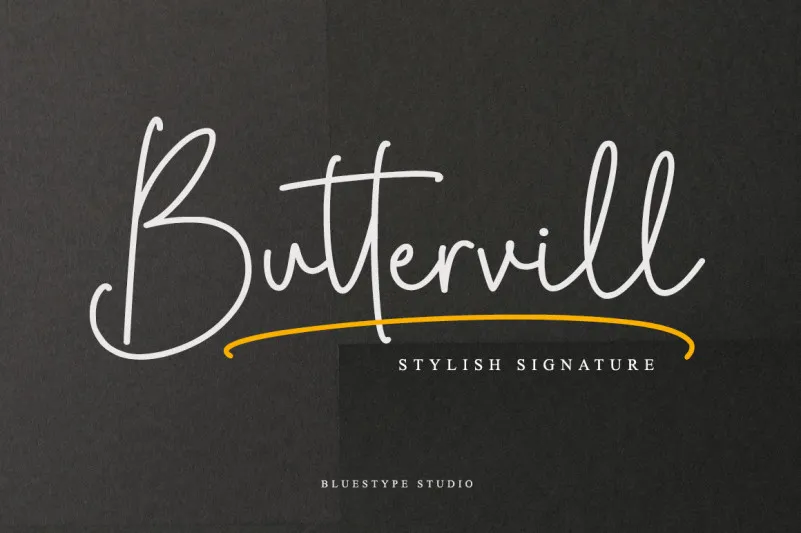
Estamos muito felizes com a sua visita ao site onde você pode baixar a Buttervill Signature Font, uma fantástica fonte de script que traz um toque pessoal para seus projetos. Esta é uma linda e simples fonte criada por f0rdesigner, inspirada no estilo da Bluestype Studio. O design desta fonte de texto faz com que ela seja perfeita para adicionar um ar autêntico a vários tipos de projetos. Que isso possa ser cartazes, convites ou até mesmo letras em sua próxima criação gráfica. A Buttervill Signature é uma combinação delicada e simples de linhas curvas robustas, que não só tornará seus materiais mais interessantes, mas também dará vida ales aos teus projetos de design. Ideal para inúmeros tipos de trabalho, desde cartazes e convites até peças de moda ou embalagens, esta fonte é uma escolha perfeita para complementar qualquer projeto criativo. Sua simplicidade e personalidade torna-a versátil o suficiente para adaptar-se a muitas diferentes necessidades, garantindo que sua identidade visual seja única e inconfundível.